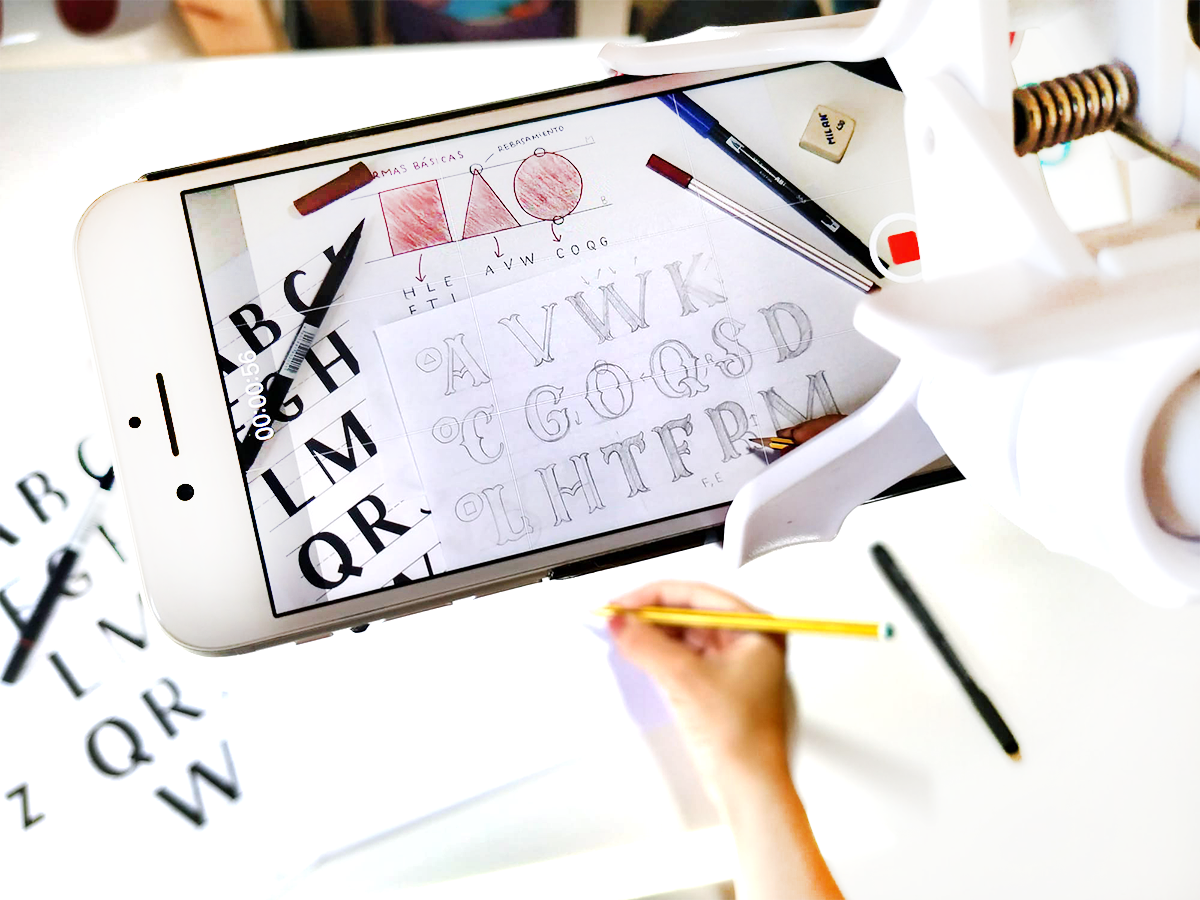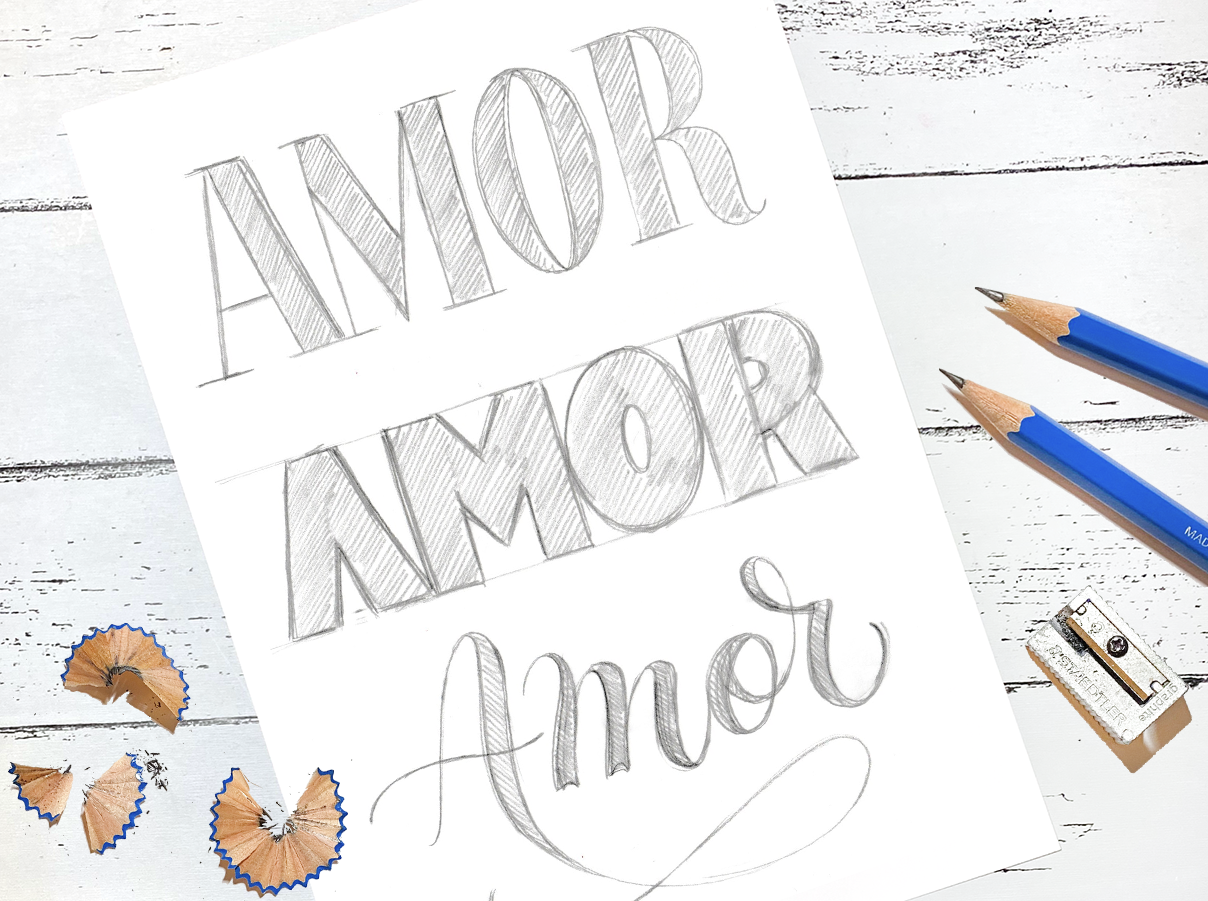
¿Por qué con lápiz?
El lettering es el arte de dibujar letras, y para crearlas podemos utilizar cualquier técnica y herramienta de dibujo, ya sean acuarelas, rotuladores, pintura acrílica, lápices de colores, o incluso dibujo digital. Pero todas ellas parten de un boceto dibujado con la herramienta más famosa de todas (y mi favorita): el lápiz.
Después de varios años enseñado en talleres presenciales y clases online, estoy convencida de que un buen boceto es imprescindible para que el lettering quede exactamente como queremos. Y muchas veces saltamos demasiado rápido a la técnica de acabado, y no conseguimos los resultados que buscamos, porque nos falla la base.
Conocer diferentes estilos, saber qué mensaje transmite cada uno de ellos, y aprender a dibujarlos correctamente, es fundamental para poder afrontar nuevos retos, como son las composiciones de lettering.
Este curso no es solo una colección de alfabetos distintos. Es, además, una guía para que entiendas cómo se construye cada uno de ellos a partir de los estilos básicos, y cómo puedes modificarlos para crear los tuyos propios según las necesidades de tus proyectos futuros.
Con alfabetos completos y ejemplos prácticos
En este curso no solo tendrás alfabetos completos de referencia, sino que cada lección está acompañada de un ejemplo para que pongas en práctica lo aprendido.
Lecciones con vídeos paso a paso para aprender a dibujar diferentes estilos de lettering, desde los más básicos hasta los más creativos.
Plantillas con alfabetos de referencia y ejemplos prácticos de cada uno de ellos, para practicar lo aprendido en cada lección.